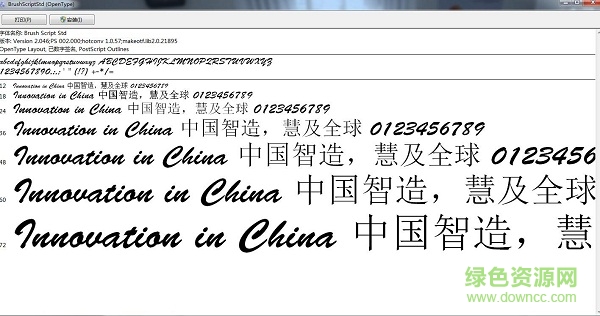
brush script std medium字體
brushscriptstd.otf字體是一款漂亮優(yōu)雅的花體字體,適合用于時(shí)尚雜志或是平面設(shè)計(jì),大家下載字體后點(diǎn)擊右鍵選擇“安裝”就可以在PS、PPT、Word等軟件中使用了!
brush script std medium字體